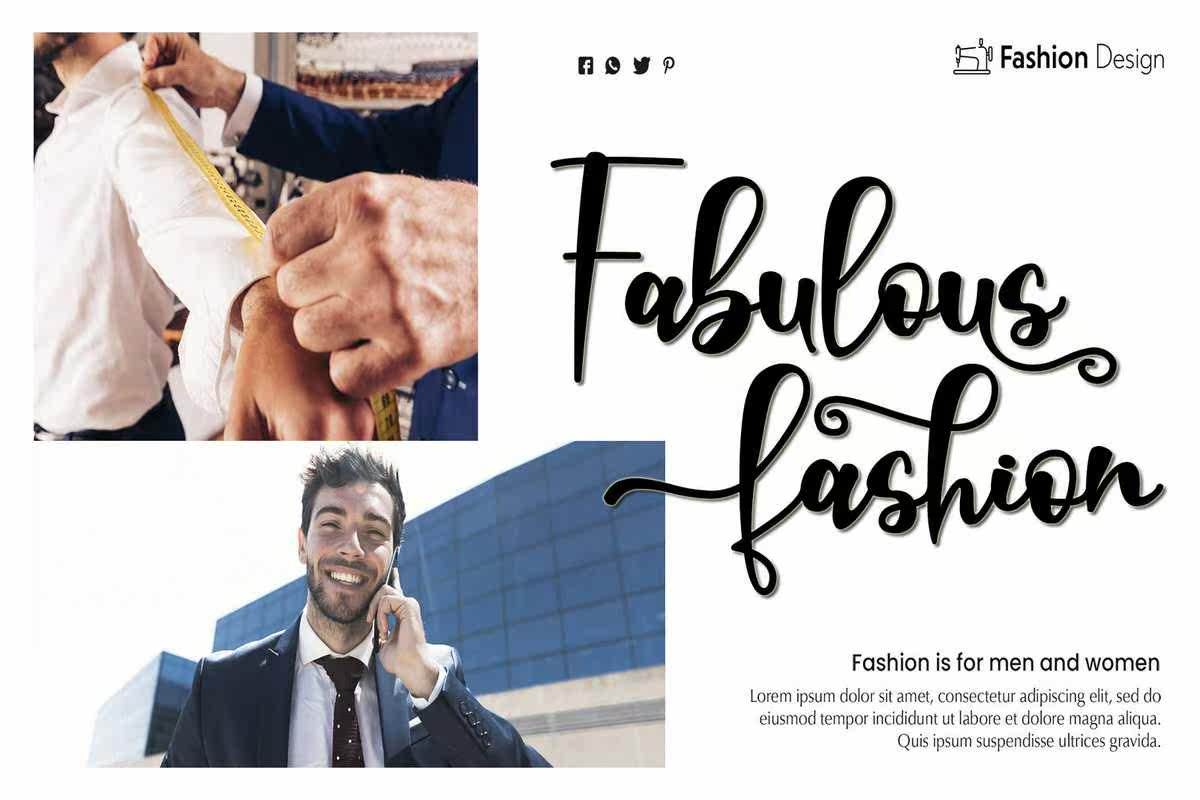
RabittafontisamodernCalligraphyFontBylettRafaStudio.Ithas Flowing Letters将为您的设计提供流动的文字,并与Fihmodel.Rabittafontispect;徽标、问候卡、包装设计、耐磨性、工艺设计、任何项目、书名、婚礼宣传、包装等。RabittaFontBylettRafaStudio。其流动字母将使您的设计符合Fihmodel。RabittaFontsPerfect;徽标、问候卡、包装设计、耐磨性、工艺设计、任何项目、书名、婚礼宣传、包装等。